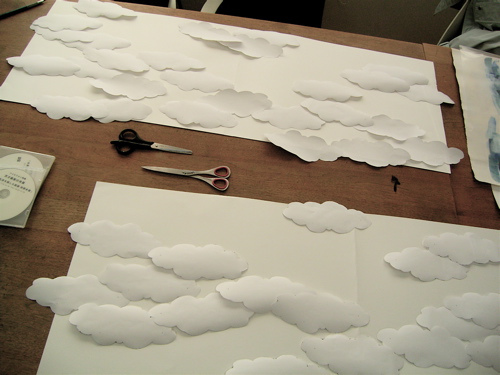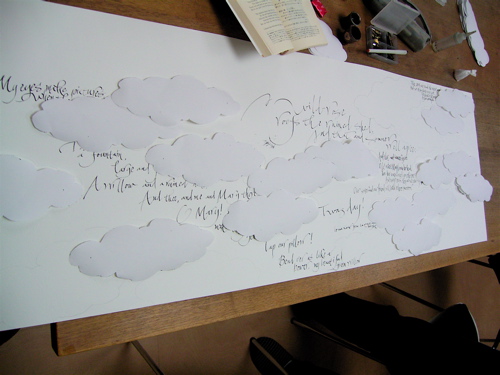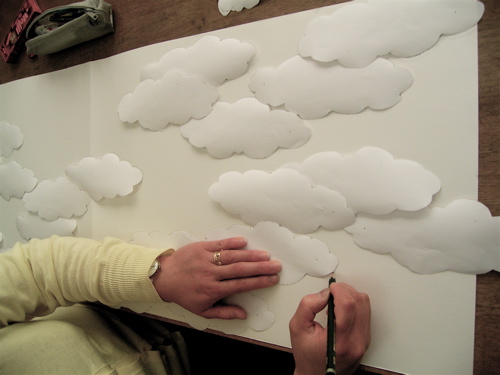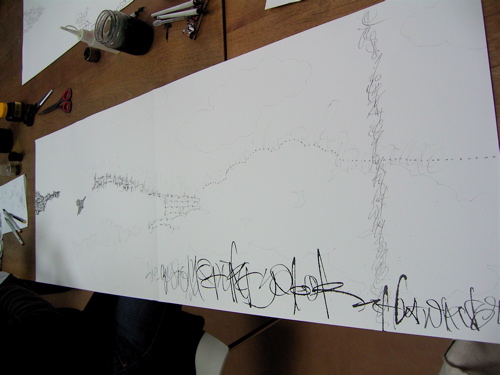
井上由季子さんのWS
3月30日の日曜日…花曇りではありましたが、心はウキウキ!
なぜなら、それは、念願かなってのモジトル主催「井上由季子さんWS」の日曜日ですもの!
モジトル主催のWSは、メルマガ登録者の
皆様限定のお楽しみでございます。
去年は、製本の山崎曜さん…手作りの
スペシャリスト繋がりで、今年は、井上
由季子さんをおよび致しました。
初めてお会いしたのですが、その優しい
人柄に一目ぼれ〜!
癒し空気は、そのままご本人からも
オーラのように発せられていたのでありました!!
井上さんのお道具!スタンプパッドは
大活躍だそうです!一色をベタで使うのではなく、混色するとか…。
最近のお気に入りは、チョッとシマーな
パールの入ったものとか…。フムフム〜チェック!
今回は、打合せの段階で「カリ人」受講ということを考慮して頂いて、カリ文字との組合せの
カードという願ってもない内容でありました。宿題もありましたよ!色んな大きさの紙にいろんな
大きさのThank you を書いて持ち寄りました。
なになに?
こんな美しく包まれたものが2種類…テーブルに並べられ…。
井上さんが「材料費のほとんどがこれにかわりました(笑)」と
おっしゃった、京都の和菓子どす!
私達のためにすごく考えて選んでくださったとか!
きゃ〜幸せ〜
左の白い包みには、京都大極殿の「そら豆のすはま」と
「玉子ぼうろ」。右の青い包みには、月餅屋の「角倉」が!おされな和菓子ですぅ〜。
井上さんの「開けてみてください〜」の一言で、総勢33名の女子が
キャハハと開ける開ける!
「角倉」は、その箱の中に三色の包みがあり中には、とても繊細な白いお菓子が…。一口ぱくり!
すぐにフワ〜って溶けてしまうその美味しさにうっとりです。
そしてまずお題は、「この角倉を頂いたお礼をカードにする!」というものでした!!
井上さんの説明が始まります。
ねっ!この笑顔…とびっきり素敵!この笑顔のまんまの方でした。
しかも関西弁が、さらに人懐っこさを倍増!!
これは、井上さんが作った角倉のわらびもちを頂いた折の
thank you カードです。30秒で作った!?…んですってぇ〜ひゃ!
包み紙を存分に使い…わらびもちが丸いので、丸の形を
選び、その紙が青いので、thank youの文字も青系を選んだ
そうです。
ここで印象深かったのは、文字を目立たせるのではなく、
頂いたものの印象の方に重点を置く。黒や赤い色で書いたら、
文字ばかりが目立ってしまいますよね…。調和の中に遊び心を加える…この判断が決めてです。
カードの紙は、ちょっときなこの色味…。もちろん、わらびもちはきな粉でお化粧しているので、
その感じが出ていますよ〜。日付は遊び心でレイアウトするそうで、最後の丸に賞味期限が
ついていて、それを使用したそうです。
100言いたいことを100言ってしまったらただの100…。100言いたいことを80で言うとそれが
120の思いを伝えることになる。
引き算の考えで最大限を表現するという
高度なテク!
でも日本人は、俳句でもそうですが、
少ない中で表情豊かな表現をするのは
得意だと思います。
井上さんの考え方にとても嬉しくなって
しまいました!
貴重なサンプルをものすごく
たさくん見せてくださり、その
一つ一つのありがとうのカタチを
説明してくださいました。
何てラッキーなことでしょう〜。
さぁ、その余韻があるうちに作業開始です!みんなどんなありがとうのカタチになるのかな?
「角倉」の方は、井上さんのアドバイスを頂きながら、2〜3枚
カードを作りました。
間に井上さんのもう一つのテクなどを説明頂き、後半は
「3分で作るありがとうのカタチ」というプレッシャーのかかる(笑)
お題で京都大極殿のお菓子からカードを作りました。
井上さんのカウントダウンで…キャーキャー(ギャーギャーかも)
言いながら作る…作る…。
みんな一人一人が自分の「ありがとうのカタチ」について
発表します。一人ずつ丁寧に井上さんがコメントをしてくれました。
すごいなぁ〜。みんなそんなこと考えていたのかぁ〜!
って同じお菓子で同じ素材なのに全く違うカタチになりましたよ。
井上さんがカリ文字が素敵だし、色使いも素晴らしいとみんなへ
温かい言葉をくださいました。実際、皆様の文字が美しかった
ですわぁ〜!井上さん線がきれい!っていうお褒めの言葉に
感激です!井上さんもカリペン買われるかもしれませんよ…今後楽しみ〜!ウフフ。
これは、3分版です!
見て見て〜!時間制限があっても
何てかわいいカード達でしょう〜!
今回は、文字の配置をバランスに
置いて大切なアドバイスを頂くことができました。シンプルが一番!でもそれは高度な遊びでもあるのですね。何だか平安貴族が和歌で歌いあった世界…はたまた、江戸の民が川柳で遊んだ世界…。そんな楽しい世界でした!
まち針は、留め具に使うのですが、先生の「よく見ると
針の頭の部分が半円ずつくっつけてある筋が見えるね…」
の一言で…。
最初はあまり気にならなかった部分が俄然見えてしまいました。
製造工程で出来る球体の真ん中一本の線…。
ひょえ〜消さなきゃ!…ということで、ネイル用のヤスリで削ったのでございます…。
細かい作業で目はシバシバ・・・。でも削ったらツルツルしていた表面がマットな感じになり
いっそう愛おしくなりました!
フィンランド製耐水航空ベニヤの登場です!
木目が美しく、大好きな素材です。
箱はこの板で覆うことにしたので、切っていかねば…。
mojitor-fさんの妄想の箱でも大活躍したこの板を
使うと何となく北欧っぽい?
この窓の中にはちっこい花瓶とチューリップが入るので
裏方さんはこの通り!
紙だけだとイメージがしにくかった窓も、航空ベニヤをつけるとこんな感じです。
白木の奥は、やはり白…。革だから質感が異なっていいかも…。
だんだんフィンランドっぽくなってきましたか?
製本教室で製本っぽくない物作り…が毎度のmojitor-h でした。
ういさんの個展
知人のOさんが、ういさんの発表する本の編集をずぅ〜っと手がけて
おいでで、昨日、個展におじゃましてまいりました。
前回は紙の作品でしたが、
今回は、おなじみのバッグ、布もの、それに加えて、布で出来た
お野菜やら、木でできたクッキー
やら、それはそれはお伽のお話し
のようで、癒される作品でした。
新しい本「FOOD?何でできてる?uiの楽しい食卓」文化出版局(ISBN978-4-579-11187-9)
の中身がドド〜ンとギャラリー全体に良い子でお座りしてます!本当に可愛い!
ういさんの美しい手からは、いろんな形が切られ、造形され、おされな小物達に大変身!
DMのバッグの柄はもちろんゆいさんがデザインしたステンシル!実物を見るとあまりに
丁寧なお仕事で「さすが〜プロ!」
今回は、たくさん、ゆいさんの作品が購入できるという幸運も!
しかも、ゆいさんがいらしたので、本にサインもして頂きました〜。ウフフ。
ほらほら…。
このピーナッツの柄に一目ぼれ!
可愛い袋!肩からもかけられるし、
底の部分の6枚はぎ?が
かわゆい形です!!
吉祥寺にあるギャラリーfeve http://www.hikita-feve.com
も本当にステキな空間です。
地下にあるパン屋さんのパンも絶品!
本当にお勧めの個展、ギャラリー、パン屋〜。
三つ一緒に楽しめるなんておとくですわ!ういさんの作品は、本当に素敵ですから!
是非、走ってください!吉祥寺は桜も満開だし〜。
童話で練習
大好きな童話はいろいろありますが、この本『The Three Robbers』は昔からお気に入りです。日本語でも出ていますよね。「すてきな3にんぐみ」とかなんとか言ったような・・・。
春ならではの香りのお茶も
今年もいただいたルピシアのお茶(おいしくいただいています!ありがとうございます)
缶もラベルもかわいいので飲み終わったあとも、例によってとってあります。
桜のラベルはとっても艶やか、華やか〜。
香りと色と温かさで、イライラや焦っている気持ちがなごんでくるのは不思議です。
作業し続けでなく、お茶の時間はやっぱり持ちたいですよね。カリグラフィーでも集中して書き続けたいときもあれば、適度に休憩をいれたほうが質があがるときもあります。
この頃やっと「休みどき」がわかるようになってきました。体力頼みができなくなった…から?
先日久しぶりにお会いした私の憧れの女性からご案内をいただいて、これはなかなか楽しそうな内容なのでちょこっとお知らせ。
紅茶の専門家によるレッスンです。
おいしい入れ方だけでなく、紅茶やお菓子のこと、イギリスのことなどなど楽しいお話がたくさん聞けると思います。実際にティータイムがあるのが楽しみです。
ティータイムレッスン
忙しい人もお茶の時間で気分を変えて、笑顔をとりもどせますように!
中林ういさんの個展です!